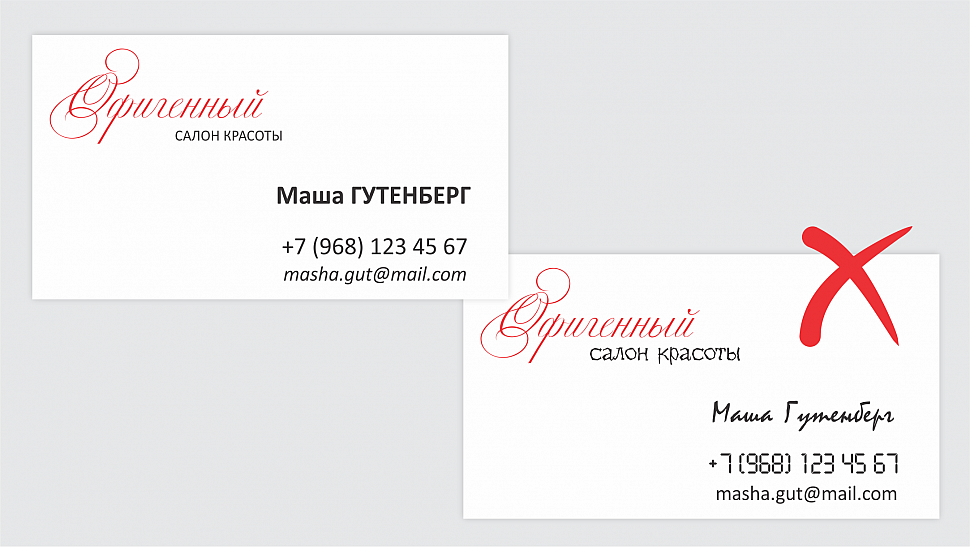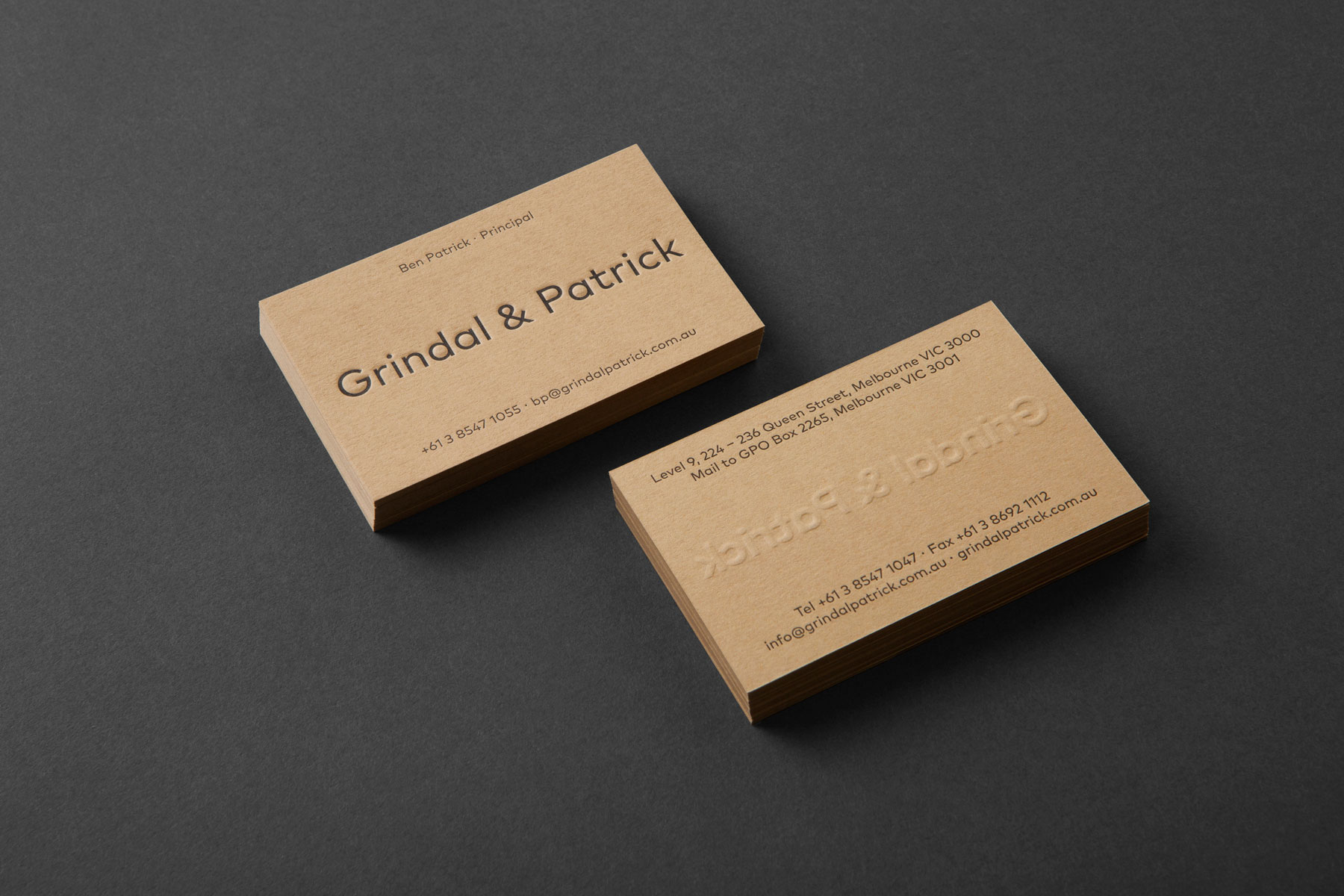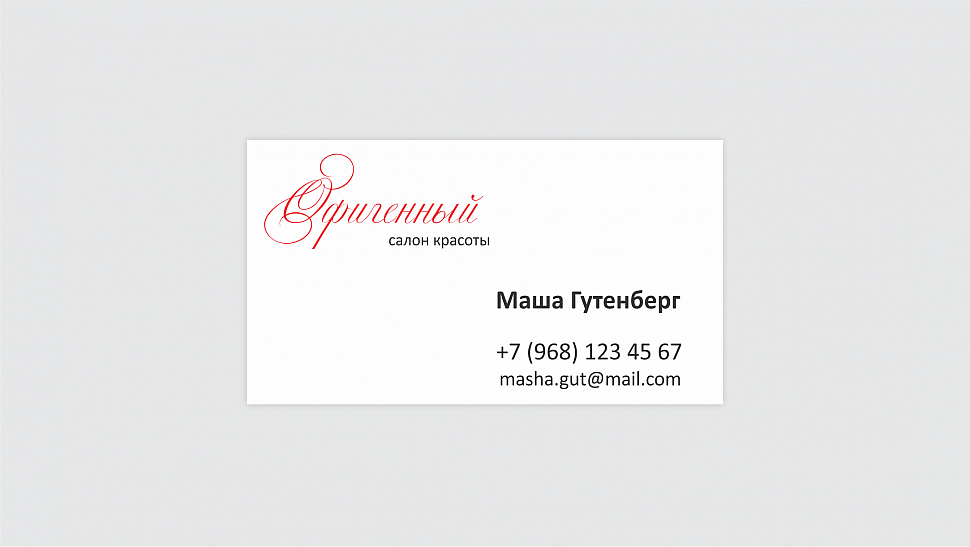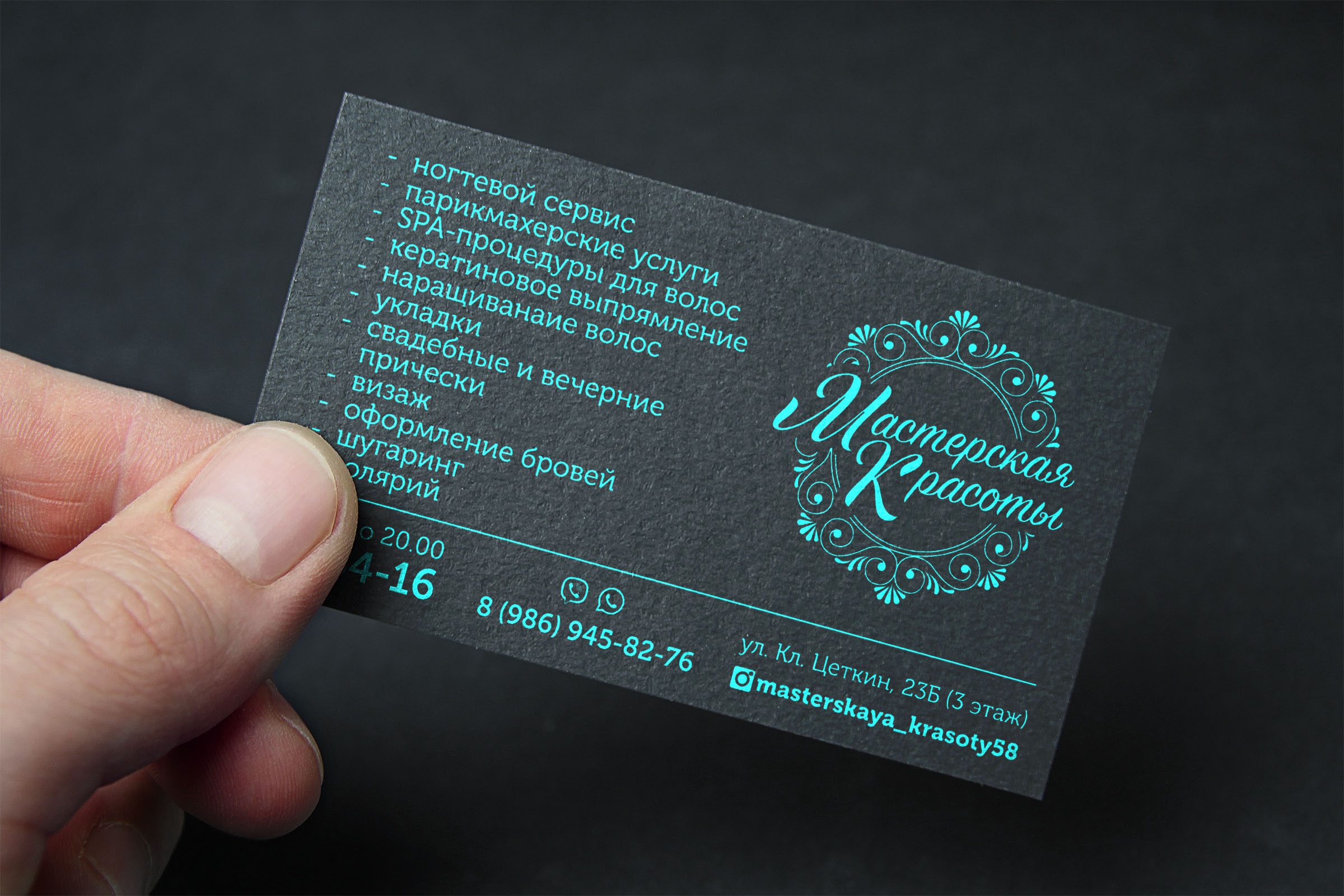
Как выбрать лучший шрифт и размер для визитной карточки
ИсточникРазмер имеет значение! Что ж, по крайней мере, мы знаем, что это верно для шрифта вашей визитки. Слишком большой, и все, что вы хотите передать, не поместится на карточке. Слишком маленький, и людям будет трудно даже прочитать то, что на нем написано!
Да, теперь вы видите, как размер имеет значение. Но не волнуйся; мы здесь не для того, чтобы информировать вас через относительные интервалы о важности размера шрифта Мы поговорим с вами о том, как выбрать лучшее размер шрифта визитной карточки.
Вы используете слишком маленькие шрифты? ИсточникДумаете, выбор мелкого шрифта позволит вам втиснуть как можно больше информации в прямоугольник размером 3.5 x 2 дюйма? Да, это служит цели. Но мы также можем заверить вас, что никто даже не попытается прочитать то, что написано на вашей карте.
Насколько маленький слишком маленький? Чтобы узнать это, сначала нужно расшифровать размер визитной карточки.
- Слишком большой, и вы занимаетесь важной визитной карточкой недвижимости
- Слишком маленький, и его трудно прочитать, даже если карту обычно рассматривают близко
Так какой именно идеальный размер?
Источник- Размер шрифта от 10 до 11 пт идеально подходит для основного текста
- Размер шрифта от 7 до 8 пт идеально подходит для контактной информации
Это не практическое правило, поскольку все зависит от дизайна.
Как дизайн играет жизненно важную роль? ИсточникВы можете определить свой размер шрифта визитной карточки обращая внимание на макет и дизайн.
- Если вы хотите подчеркнуть информацию, выберите более крупные и смелые шрифты
- Если вам не хватает места, подумайте о выборе двухсторонних карт
Выбор наилучшего размера шрифта вашей визитной карточки в конечном итоге зависит от:
- Обрати внимание на что собой представляет дизайн карты
Это необходимо изменить и отрегулировать после того, как вы примете во внимание макет визитной карточки.
- Принять к сведению рекомендации по брендингу
Обратите внимание на определенный тип шрифта, который может использовать ваш бренд. Это может выглядеть не очень хорошо, когда он маленький
- Содержание является ключевым
Если в вашей карточке достаточно контента, не используйте меньший размер шрифта. Выберите жирный шрифт, если это важно
Шрифты, которые помогут вам набрать с визитной карточкойЕсть шрифты, которые явно выигрывают, если заметить их на визитной карточке. Если у вас нет особенностей фирменного стиля, которым нужно следовать при выборе шрифтов, вот несколько стилей шрифтов, из которых вы можете выбрать. Они определенно делают чтение менее трудоемким занятием.
Без засечек- Если шрифт достаточно толстый, легче всего читать без засечек
- Это не идет с избыточными расцветами
- Вы получаете прямые, аккуратные и чистые линии, которые оставляют вас без беспорядка текста
- Вы можете использовать этот шрифт в меньших размерах и не потерять много
Полезный совет: Sans Serifs — идеальный шрифт для профессиональных визиток.
Он поставляется с закругленными краями и аккуратными прописными буквами, которые придают ему стильный и формальный вид.
- У шрифтов с засечками есть небольшие декоративные полоски на концах каждого персонажа
- Это может быть немного сложнее, чем с засечками
- Это более формально, как печатная машинка
- Эти шрифты обычно больше, чем обычные шрифты без засечек
Полезный совет: Times New Roman также является эффективным стилем шрифта. Легко читать. Несмотря на то, что это более распространенный шрифт, вы можете использовать варианты и параметры стиля, такие как курсив, чтобы добавить более уникальный вид. Используйте его для более простых участков вашей карты. Например, контактная информация.
Скрипты или специальные шрифты- Скрипты и некоторые специальные шрифты трудно читать
- Используйте их в умеренных количествах, достаточно просто, чтобы правильно представить свой бренд
- Сделайте их большими по размеру, чтобы их было легко читать
Он имеет изогнутые буквы, которые придают игривый вид. Это идеально подходит для неформальной аудитории.
Кроме того размер шрифта визитной карточки, вам также необходимо принять во внимание цвета, концепции, шрифт, изображения, формы и шрифты.
Материалы- Если вы собираетесь использовать обычный материал, лучше всего подойдут бумага, картон или пластик.
- Если вы ищете нетрадиционные материалы, выберите что-то подходящее для вашего бизнеса
- Выберите цвета, которые соответствуют вашему бренду
- Цветовой режим, который вы используете для печати, также важен
- Посмотрите, что это систематически планируется и подробно
- Знайте свою целевую аудиторию и как вы хотите, чтобы они смотрели на ваш бизнес
- Займитесь легко читаемыми шрифтами
- Подумайте об использовании мощных шрифтов
- Ограничьте ваши стили текста двумя типами шрифтов
- При выборе изображения держите позицию и общий баланс вашей визитной карточки в приоритете
Карты с засечками, управляемыми символами
— Прекрасный женственный дизайн для косметического бренда ручной работы. Визитная карточка от J U L I A M A R I E. Этот штампованный дизайн от Cocoa Branding выглядит старомодным, но в то же время совершенно модным. Эта визитка для фотографического бизнеса чистая, но забавная. Дизайн Prozmajevski для The Regular Phil Picture Takers. Эта визитная карточка ипотечной корпорации величественна, но не скучна. Design by Rose »для Nation One Mortgage. Простая и гламурная, эта карта идеально подходит для модного бренда.Визитная карточка от design_C для A Life In The Fashion Lane.